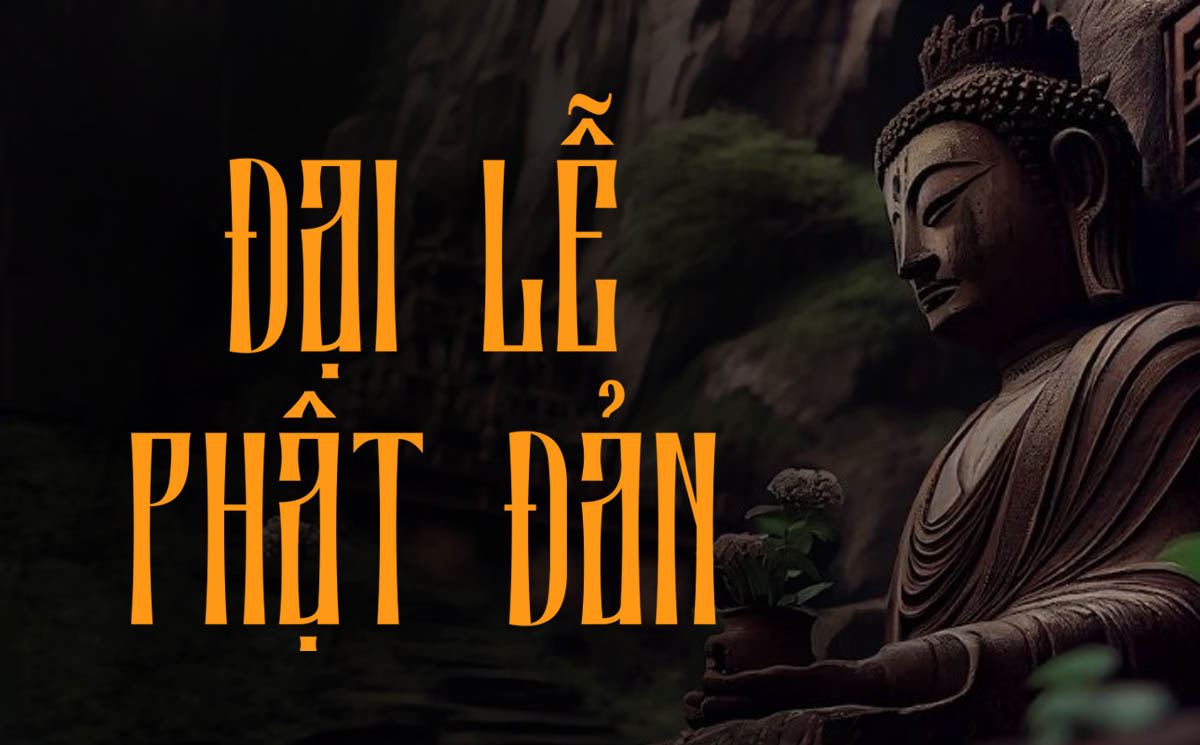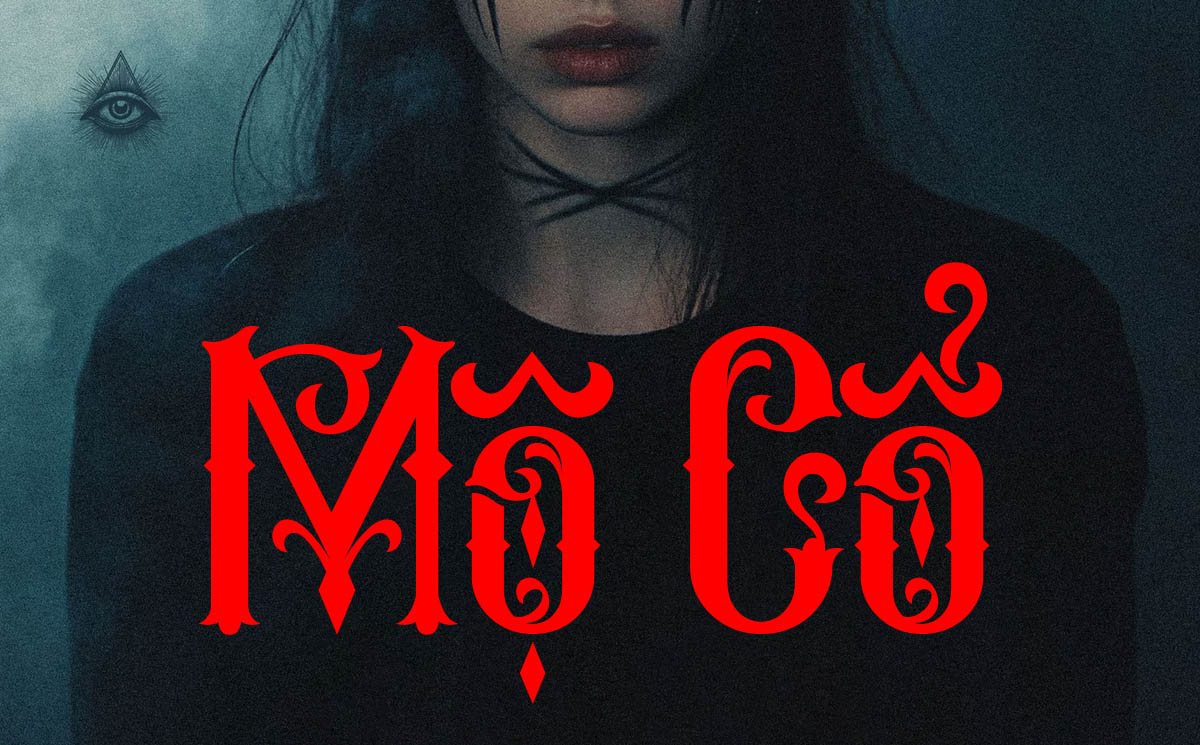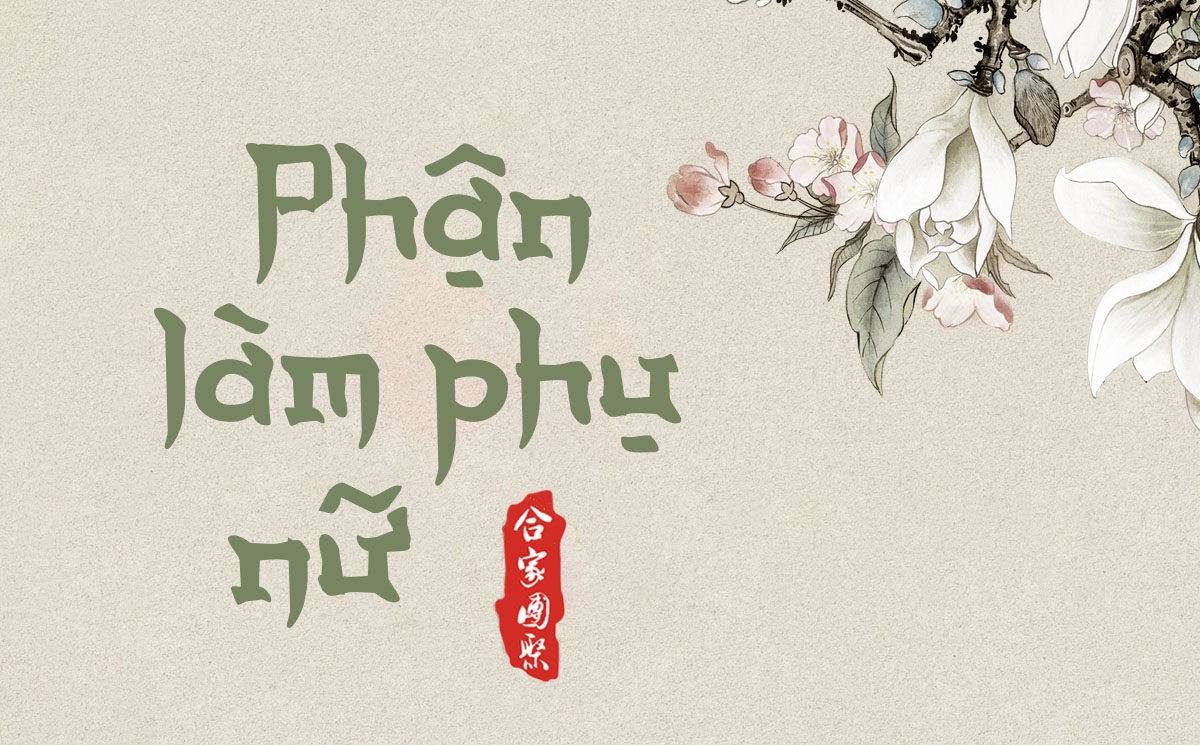
Top 14+ Font Chữ Cổ Trang Việt Hóa Đẹp Nhất 2025 Dành Cho Thiết Kế
Khám phá 14+ font chữ cổ trang Việt hóa đẹp nhất 2025 – mang đậm tinh thần Á Đông, phù hợp thiết kế poster, thư pháp, phim kiếm hiệp, Tết và ấn phẩm truyền thốn
Bạn đang tìm một kiểu chữ mang hơi thở cổ xưa, phù hợp với thiết kế poster phim, tranh thư pháp hay ấn phẩm truyền thống? Font chữ cổ trang chính là lựa chọn lý tưởng để tái hiện vẻ đẹp văn hóa Á Đông – từ nét bút thư pháp mềm mại đến kiểu dáng mạnh mẽ, đậm chất kiếm hiệp. Trong bài viết này, fontdep.vn giới thiệu đến bạn bộ sưu tập font cổ trang Việt hóa đẹp nhất 2025 – dễ dùng, đầy đủ dấu tiếng Việt. Cùng khám phá và tải về ngay bên dưới!
Phông chữ cổ trang là gì?
Phông chữ cổ trang là những kiểu chữ được thiết kế mang đậm tinh thần hoài cổ, lấy cảm hứng từ thư pháp, văn hóa Hán – Việt xưa và phong cách nghệ thuật phương Đông. Không chỉ đơn thuần là những đường nét uốn lượn hoặc góc cạnh mạnh mẽ, font cổ trang còn thể hiện bầu không khí trang nghiêm, linh thiêng, và đôi khi là sự phóng khoáng của một thời đại đã qua.
Trong bối cảnh thiết kế hiện đại, việc sử dụng font cổ trang giúp khơi dậy cảm xúc, kết nối văn hóa và tạo ra điểm nhấn khác biệt trong những sản phẩm mang yếu tố truyền thống, từ poster phim kiếm hiệp cho đến các ấn phẩm thư pháp, banner Tết hay tranh nghệ thuật dân gian.
Top 14+ font chữ cổ trang Việt hóa đẹp nhất 2025
DFVN Qojarun Regular – Cổ Trang, Mềm Mại
DFVN Qojarun Regular là một kiểu font chữ cổ trang mang dáng vẻ mềm mại nhưng có chút phá cách hiện đại. Các đường nét uốn cong nhẹ ở đầu và chân chữ tạo cảm giác thư pháp cách điệu, gợi nhớ đến kiểu chữ viết tay trong các ấn phẩm văn học cổ. Khoảng cách chữ thoáng, độ nghiêng nhẹ ở một số nét khiến tổng thể trở nên uyển chuyển mà vẫn rõ ràng, dễ đọc. Font rất phù hợp cho tiêu đề truyện kiếm hiệp, poster cổ phong hoặc các thiết kế mang yếu tố văn hóa truyền thống Đông Á.
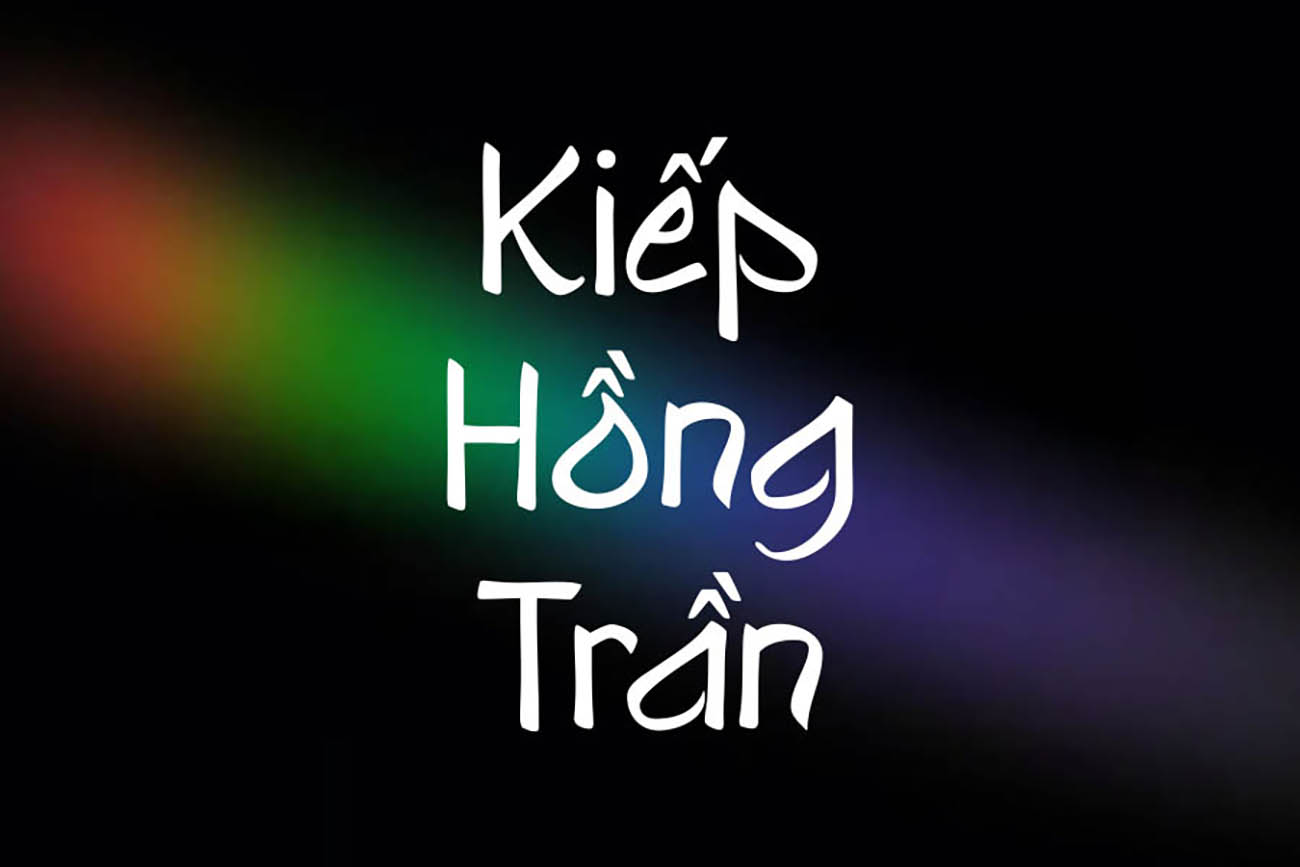
NVN Morning Calm – Cổ Trang, Sang Trọng
NVN Morning Calm là kiểu font chữ cổ trang mang dáng dấp vương giả, được thiết kế với cấu trúc hình khối vuông vức, góc cạnh rõ nét và mang đậm phong cách cung đình phương Đông. Từng chữ cái đều có dáng đứng vững vàng, nhấn mạnh cảm giác quyền lực và trang trọng. Font phù hợp cho các thiết kế về Tết, chủ đề hoàng cung, lịch sử hay lễ hội truyền thống, đặc biệt là các dự án cần yếu tố trang nghiêm, cổ kính nhưng vẫn hiện đại và dễ đọc.
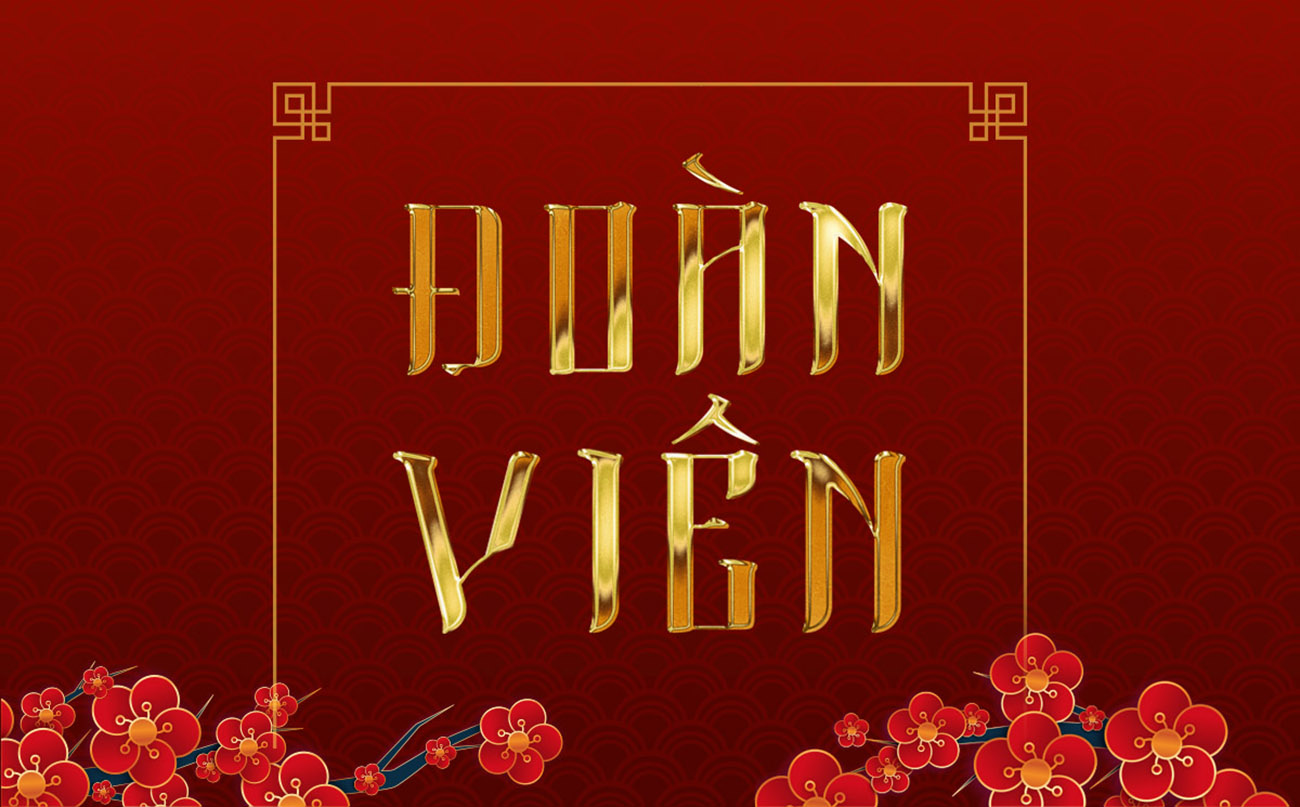
SVN Bestagrach – Cổ Trang, Lãng Mạn
SVN Bestagrach là kiểu font serif cổ trang mang dáng dấp mềm mại và đầy chất thơ. Các nét chữ được thiết kế thanh mảnh với phần đuôi uốn cong nhẹ, tạo cảm giác hoài niệm và yên bình. Font phù hợp cho các thiết kế về làng quê, hồi ức, phim ảnh cổ điển hoặc các dự án cần chất mơ mộng pha chút cổ kính. Đây là lựa chọn tuyệt vời khi bạn muốn kết hợp giữa sự cổ điển tinh tế và cảm xúc nhẹ nhàng trong thiết kế.
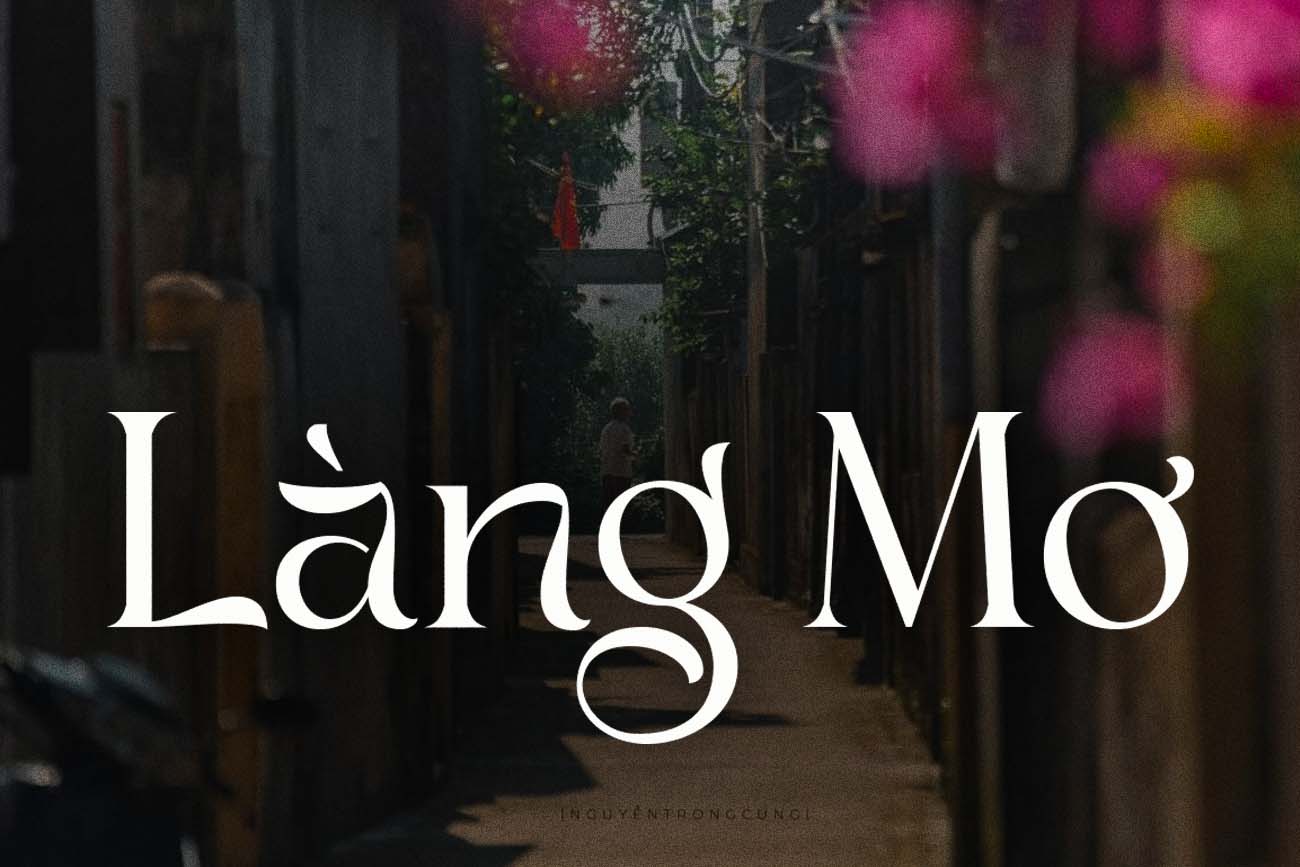
TH Hidayatullah – Cổ Trang, Trang Nghiêm
TH Hidayatullah là kiểu font cổ trang mang phong cách Gothic Á Đông, kết hợp giữa sự uy nghiêm và đường nét mềm mại. Chữ cái được tạo hình cầu kỳ với các móc và bo góc đặc trưng tạo sự trang trọng như trong kinh sách cổ hoặc tiêu đề liên quan đến tôn giáo, tâm linh. Font tôn lên vẻ trang nghiêm, rất lý tưởng khi dùng trong thiết kế thư pháp, tranh thiền hay các sự kiện văn hóa tâm linh.
- Tác giả gốc: Anthonie Van Hayu (ARToni)
- Việt hóa bởi: Phạm Sơn - Admin S99, Fontdep.vn
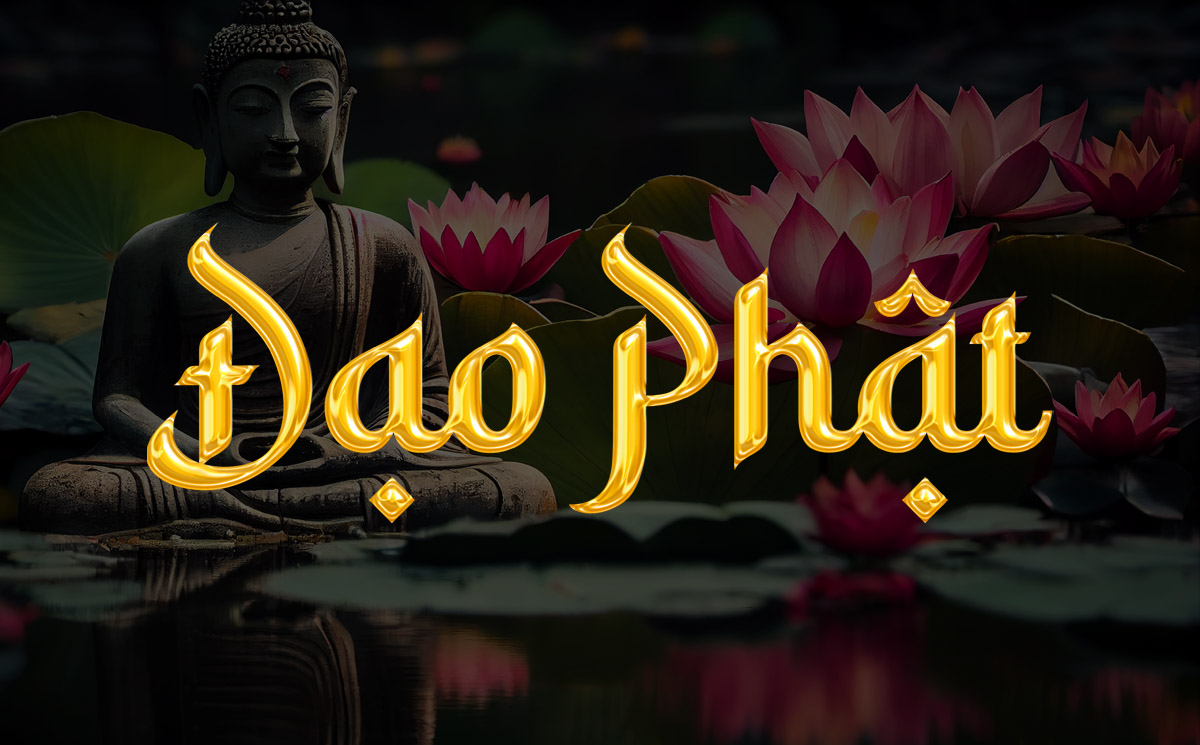
FZ Tiểu Tự – Thư Pháp, Bay Bổng
FZ Tiểu Tự là kiểu font thư pháp cổ trang nổi bật với các nét viết tay mềm mại, phóng khoáng và giàu biểu cảm. Kiểu dáng chữ mô phỏng bút lông truyền thống, có độ nhấn nhá ở đầu và đuôi nét tựa như dòng mực đang lướt trên giấy dó. Font chữ này là sự lựa chọn lý tưởng cho thơ, tranh chữ, tiêu đề sách hoặc các thiết kế lấy cảm hứng từ nghệ thuật thư pháp Đông Á, truyền tải tinh thần thanh thoát và lạc quan.
- Tác giả gốc: Đức Thủy - Admin Font Zin
- Việt hóa bởi: Đức Thủy - Admin Font Zin
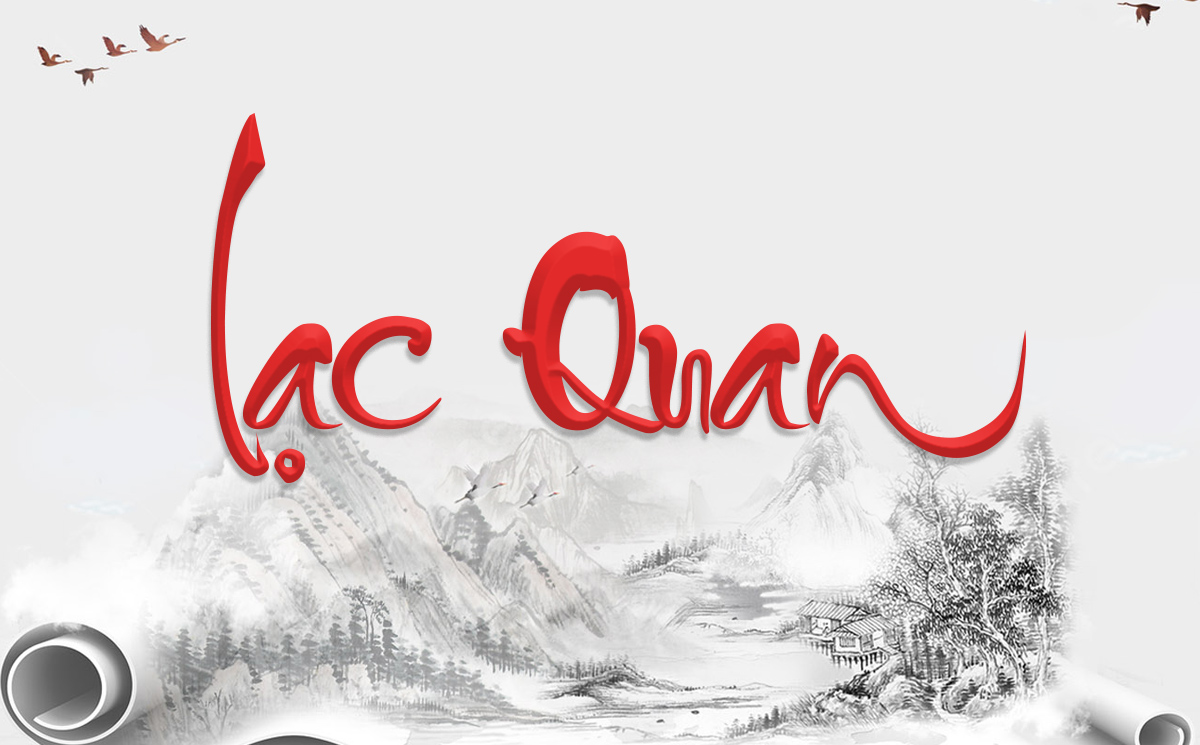
SVN Nubya – Cổ Trang, Cứng Cáp
SVN Nubya là một kiểu font cổ trang với cấu trúc hình học độc đáo, mang dáng vẻ vững vàng và trang trọng. Các chữ cái được tạo hình khối đứng, góc cạnh rõ ràng, mang đến cảm giác hiện đại nhưng vẫn gợi nhớ đến kiến trúc và mỹ thuật cung đình Á Đông. Font phù hợp cho thiết kế biển hiệu chùa, bìa sách văn hóa, tiêu đề phim dã sử hay các dự án cần thể hiện sự nghiêm trang, bản sắc truyền thống kết hợp nét đương đại.
- Tác giả gốc: Ajax Piper
- Việt hóa bởi: STYLEno.1
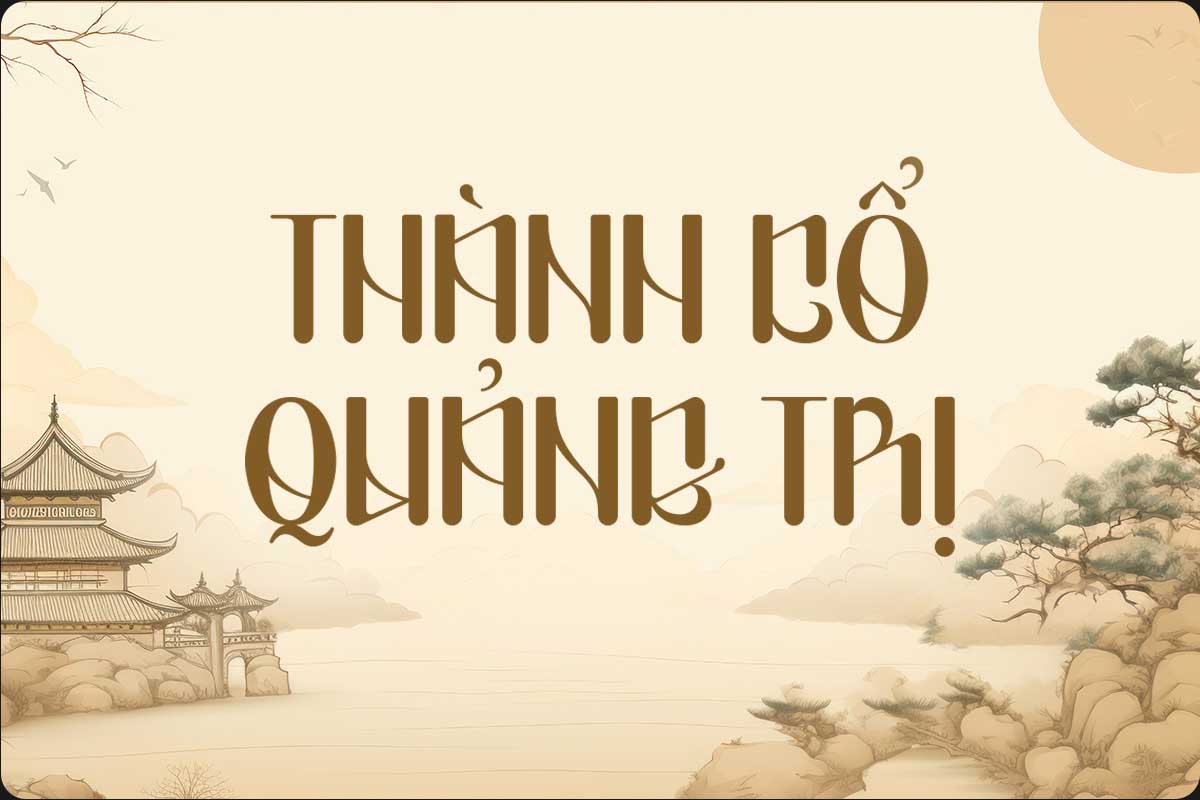
Zahra – Cổ Trang, Cách Điệu
Zahra là kiểu font chữ cổ trang độc đáo với đường nét cách điệu mềm mại ở đầu và cuối ký tự, mang phong thái thư pháp nhưng vẫn giữ được sự cân đối hiện đại. Các nét kéo dài cong vút tạo cảm giác bay bổng, gợi lên hình ảnh cảnh sắc cổ phong, đậm chất thơ. Kiểu chữ này thường được ứng dụng trong tiêu đề truyện kiếm hiệp, poster tranh sơn thủy hoặc những thiết kế tái hiện vẻ đẹp huyền ảo, nhẹ nhàng của văn hóa Á Đông.
Có thể chia thành 4 nhóm: nhẹ nhàng, mạnh mẽ, nghệ thuật và Á Đông.
Font Việt hóa khác gì font Trung Quốc gốc?
Font Việt hóa có đầy đủ dấu, dùng được trong văn bản và thiết kế thuần Việt.
Dù bạn là designer chuyên nghiệp hay chỉ đơn giản là người yêu văn hóa truyền thống, việc lựa chọn một font cổ trang phù hợp có thể giúp thiết kế của bạn "nói lên một câu chuyện" mà người xem cảm nhận được ngay từ ánh nhìn đầu tiên.